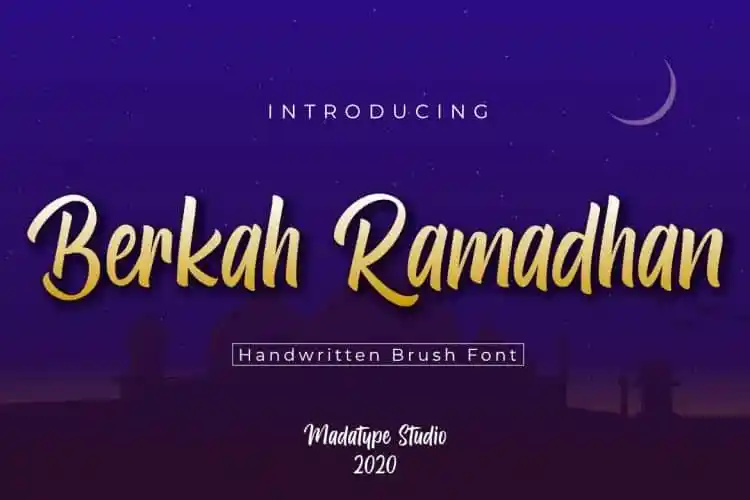
Berkah Ramadhan Script Font – Fonte Grátis
Berkah Ramadhan Script Font
A ‘Berkah Ramadhan Script Font’ é uma criação digital que traz consigo uma textura única e vibrante, inspirada na escrita de sinais de vias antigas e vintage, feitos a mão. Esta fonte Brush oferece um toque autêntico ao design gráfico, permitindo aos designers criar mensagens memoráveis e elegantes em projetos de arte digital. O processo criativo por trás desta fonte é uma história fascinante, inspirada na riqueza e no desfile da escrita manuscrita dos tempos antigos. A textura que adquirem esses sinais de via antigas transmitem a sensação de um passado distante, entrelaçado com o presente através do design digital moderno. ‘Berkah Ramadhan Script Font’ é uma peça perfeita para designers em busca de adicionar um toque histórico e autêntico ao seu trabalho. Com sua textura vibrante, esta fonte Brush permite aos criativos incorporar elementos únicos de arte em seus trabalhos, como se cada letra fosse atraída pela magia das caligrafias antiguas. Seja para revistas, letras sobrepostas ou qualquer outro projeto que valorize a história e o design, ‘Berkah Ramadhan Script Font’ oferece uma solução perfeita para esse requisito.